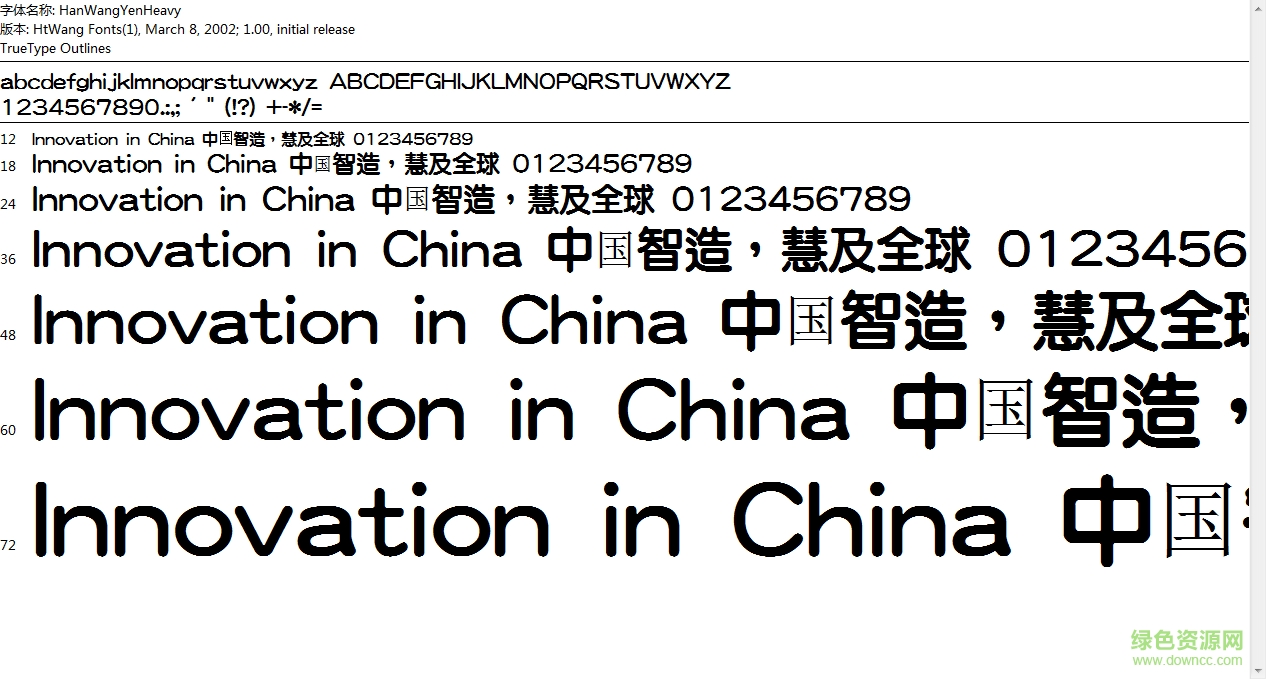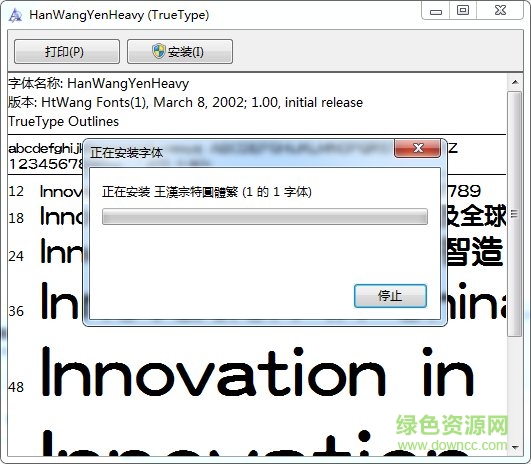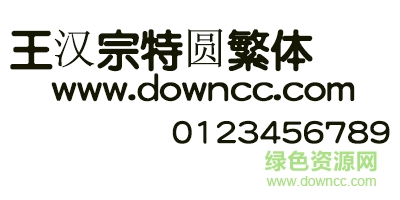
王漢宗特圓繁體是繁體字體中使用比較多的一個(gè)字體資源。字體為粗圓形狀,輸出的字體看起來(lái)比較豐滿(mǎn)圓潤(rùn)!可以用來(lái)設(shè)計(jì)一些醒目的文字內(nèi)容。需要的用戶(hù)歡迎下載使用。
王漢宗特圓體是比較常用的一款圓體字體,此款字體采用粗線(xiàn)條,給人感覺(jué)比較較圓潤(rùn),整體效果非常的出眾,支持中文、英文、數(shù)字輸入,喜歡的朋友快來(lái)綠色資源網(wǎng)下載吧!